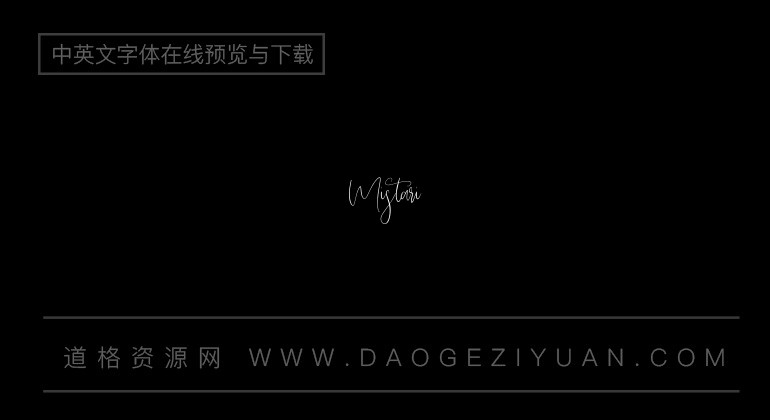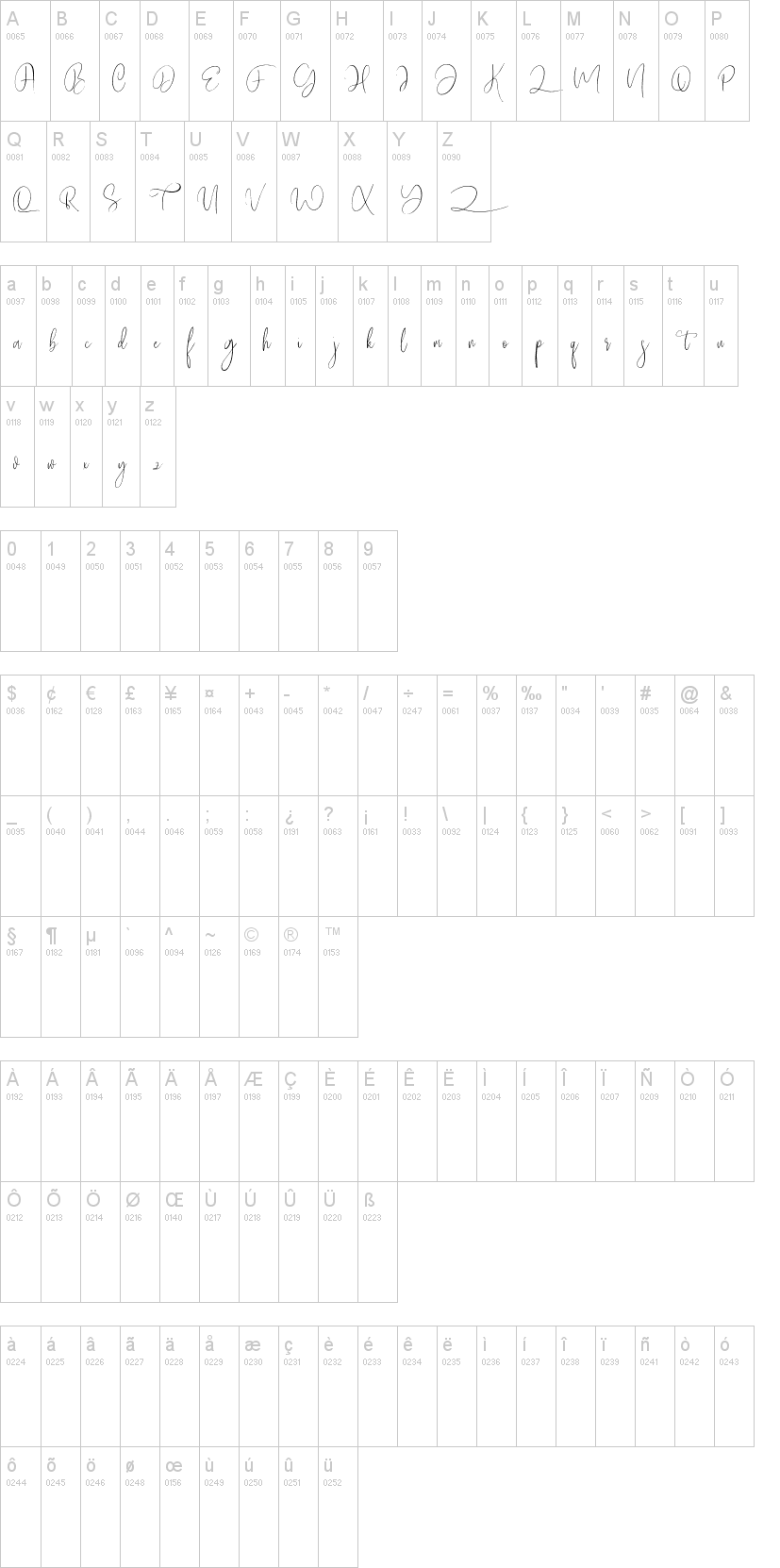
Mistari字体是一款简约优雅的英文字体,它的设计灵感来自于古希腊的古典文学。它的字形轮廓简洁大方,是一款易读性高的英文字体,适用于各种文字组合,可以给人以清新、舒适的视觉感受。 Mistari字体可以用于广告、宣传、网页、书籍、杂志等各种印刷品的设计中,也可以用于商标、标识等设计中,具有很高的实用性。内容介绍
Mistari是一款非常不错的手写艺术字体,具有很好的视觉感,适合于文化类的宣传设计、商业类品牌的广告和产品包装设计以及个性化文字排版等较多场景。